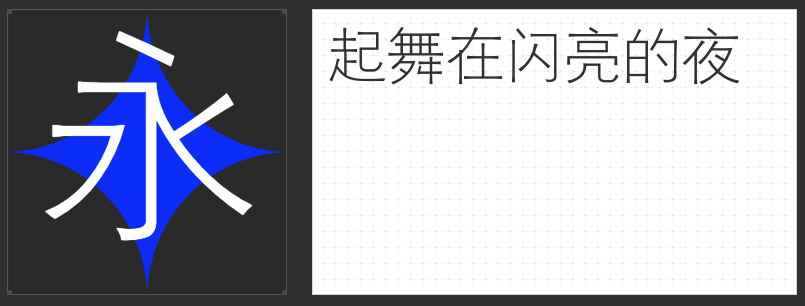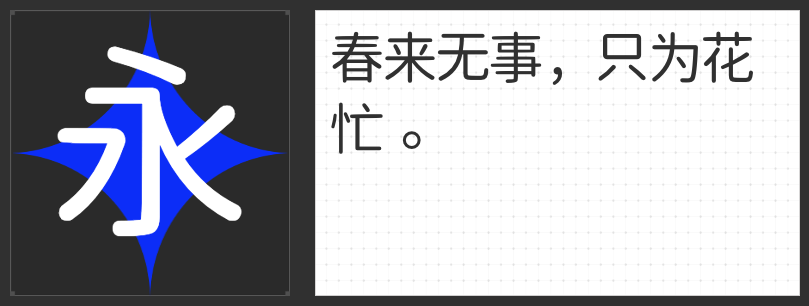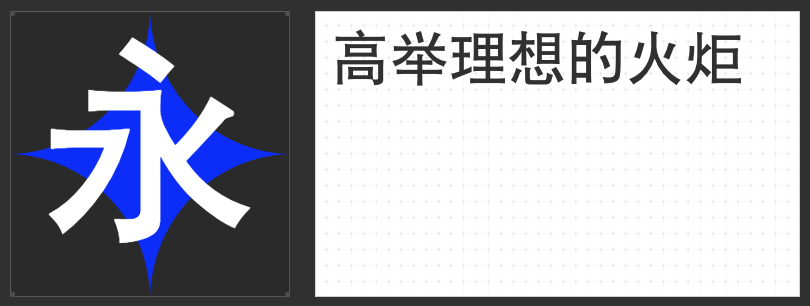
特朗普演讲遇袭登上热搜,适合新闻的黑体字体推荐
在撰写严肃正经的新闻时,选择合适的字体至关重要,它不仅关乎文章的整体美感,更直接影响到信息的传达效果和读者的阅读体验。以下推荐几种适用于新闻的字体:
励字志向黑简 常规融合了圆体与黑体的精髓,既保持了黑体的稳重与大气,又在笔画拐角处增添了外圆角,使得字体在保持结构稳定的同时,增添了几分灵动与活力。这种设计不仅提升了字体的辨识度,更赋予了新闻内容以积极向上的精神内涵,激励读者不断前行。
在新闻排版中,励字志向黑简 常规能够清晰地传达信息,无论是标题还是正文,都能以最佳的视觉效果呈现给读者。其简洁明快的线条和饱满的字面,使得新闻内容更加紧凑有力,让读者在阅读过程中感受到新闻的力量与温度。
励字细黑简以其纤细而不失力量的线条,展现出一种独特的优雅与精致。在新闻标题中,它能够以简洁明了的方式,迅速抓住读者的眼球,传达出新闻的核心信息。而在正文中,其细腻的笔触则让文字更加流畅易读,使读者能够轻松沉浸在新闻内容之中。
此外,励字细黑简还具备极高的辨识度,即使在快速浏览的情况下,读者也能迅速识别并理解文字内容。这种特性使得它在新闻排版中占据了重要位置,为新闻内容的呈现提供了有力的支持。
也字工厂万能黑体以黑体为基础,通过精细的设计调整,既保留了黑体的稳重与力量感,又增添了现代与时尚的气息。其笔画粗细分明,结构紧凑有力,使得新闻标题更加醒目,正文内容更加清晰易读。无论是严肃的时政新闻,还是轻松的社会报道,也字工厂万能黑体都能完美适配,展现出独特的视觉效果。
更重要的是,也字工厂万能黑体具备极高的兼容性和可编辑性,能够满足不同新闻的排版需求。无论是线上新闻印刷品,还是新闻短视频,这款字体都能呈现出最佳的阅读体验。
在新闻传播的广阔领域,字体的选择直接关系到信息的传递效果与读者的阅读体验。在众多字体中,励字黑体简繁凭借其独特的风格与广泛的适用性,成为新闻报道中的精准之选。
这款字体融合了黑体的稳重与简繁字的文化底蕴,保留了黑体在新闻标题中的醒目效果,展现了汉字的独特魅力。无论是简体字的清晰明了,还是繁体字的古朴典雅,励字黑体简繁都能完美呈现,为新闻报道增添了一份独特的韵味。
综上所述,都是撰写严肃新闻时的优选。它们各自具有独特的风格特点,能够根据不同的新闻内容和排版需求进行灵活搭配,以达到最佳的视觉效果和阅读体验。